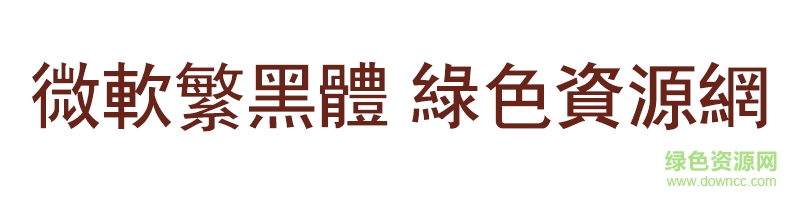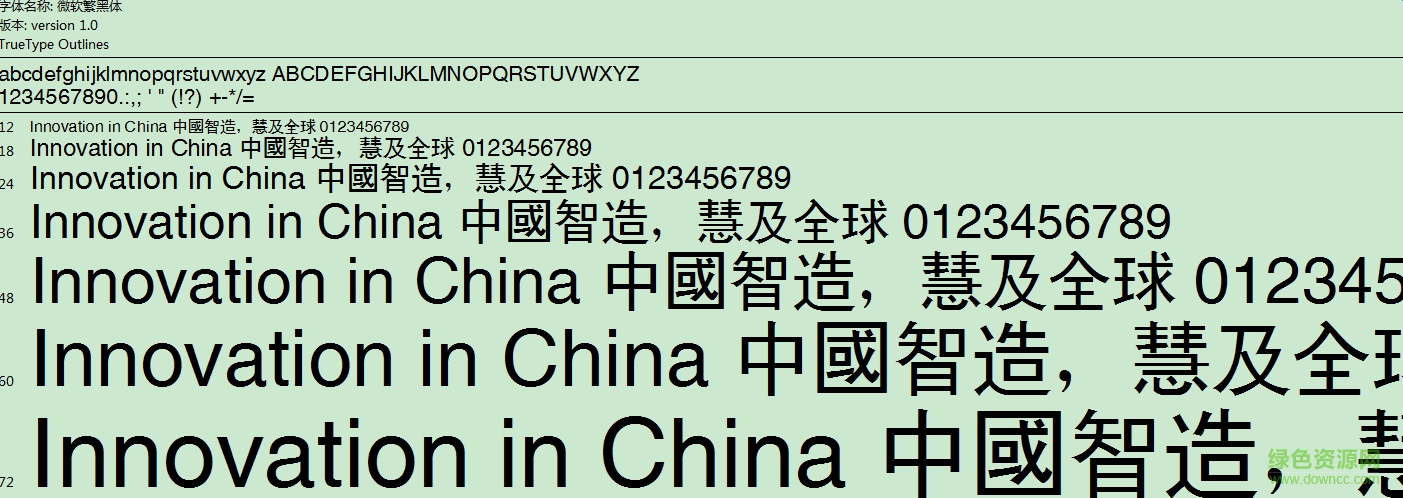
微軟繁黑體結(jié)構(gòu)嚴(yán)謹(jǐn)、字形端正、筆畫(huà)橫平豎直,字形風(fēng)格中正剛肅,筆畫(huà)首尾巧用圓角,令其在古樸沉厚的同時(shí)又不失和柔儒雅之風(fēng)。適合應(yīng)用于書(shū)籍裝幀設(shè)計(jì)、包裝設(shè)計(jì)、海報(bào)設(shè)計(jì)、網(wǎng)頁(yè)設(shè)計(jì)等應(yīng)用。